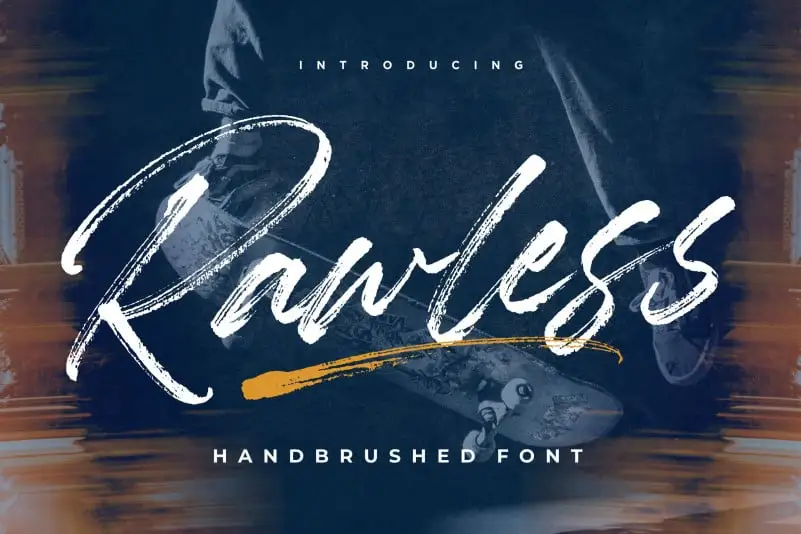
Rawless Natural Handbrushed Font
A Rawless Natural Handbrushed Font é perfeita para criar uma experiência visual atraente e autêntica, ideal para diversas aplicações digitais. Sua textura natural e toque de desenho artesanal fazem-a um recurso essencial tanto para design de embalagens de produto quanto para criação de logotipos, convites e identidade visual. Com seu estilo de escrever por conta própria, a Rawless oferece uma opção versátil para qualquer projeto que exija um toque único e imersivo, seja em impressões estilizadas ou em aplicativos digitais. Essa fonte é perfeita para design de marca, identidade visual em editoriais, criação de mídias sociais e até mesmo para mensagens pessoais criadas sobre um fundo, com seu estilo natural que transmite uma sensação de frescor e autenticidade.